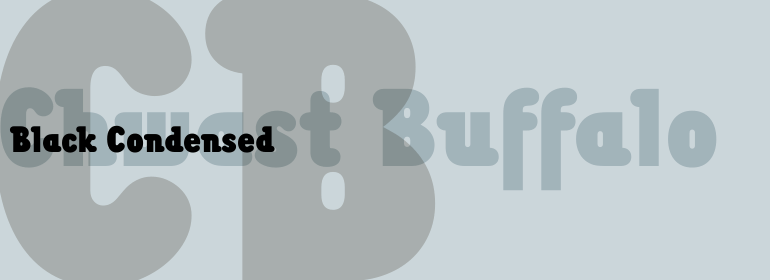
Chwast Buffalo®
Chwast Buffalo®,这款字体结构工整、笔画清晰,兼顾美观与易读性,适用于标题、正文、海报、包装、LOGO 等多种场景。字形优雅稳定,风格百搭耐看,适配日常排版与创意设计,让文字呈现更舒适、更具质感。Chwast Buffalo®一笔一画,皆是细节,以均衡的比例、流畅的线条打造舒适视觉体验,字形端正大气,风格简约现代。无论是商业设计、品牌宣传还是日常排版,都能轻松驾驭,让文字更有格调与力量。Chwast Buffalo®字体下载。
字体品牌: Linotype(Monotype) 设计师:Chwast,Seymour 字体分类:衬线体 字体属性:外文 字符集:Unicode 发布时间: 2018